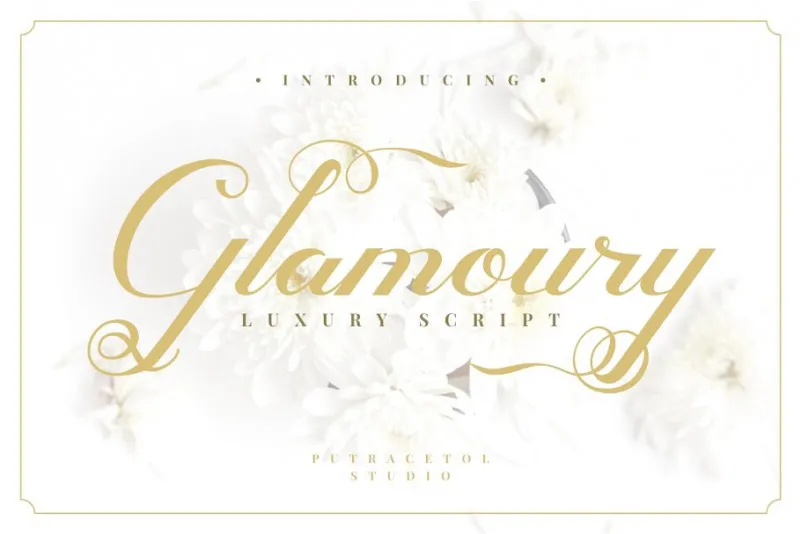
Glamoury Script Font – Fonte Grátis
Glamoury Script Font
A Glamoury Script Font é uma escolha perfeita para designers que valorizam elegância natural e modernidade. Introduzida pela M.0Type, esta fonte vem com um toque moderno que combina glamour, realeza, elegância clássica e beleza decorativa em seu design. Ela traz uma variedade de alternativas do tipo aberto, facilitando a criação de escritas únicas e encantadoras. A Glamoury é perfeitamente adequada para o uso em cabeçalhos, capas, convites, etiquetas, outdoors, logotipos, citações, embalagens de produtos, marcas, materiais de merchandising, mídia social e cartões de agradecimento. Esta font traz um toque diferenciado para seu design, tornando-o único e impecável.